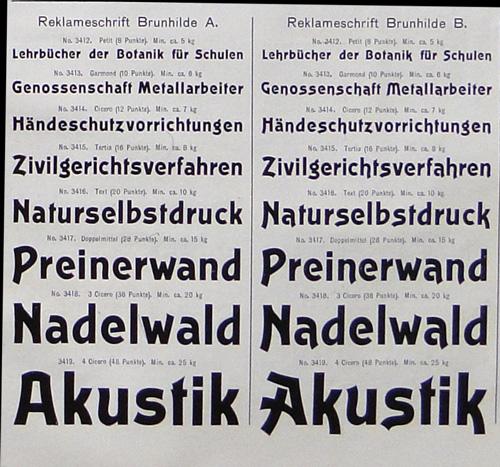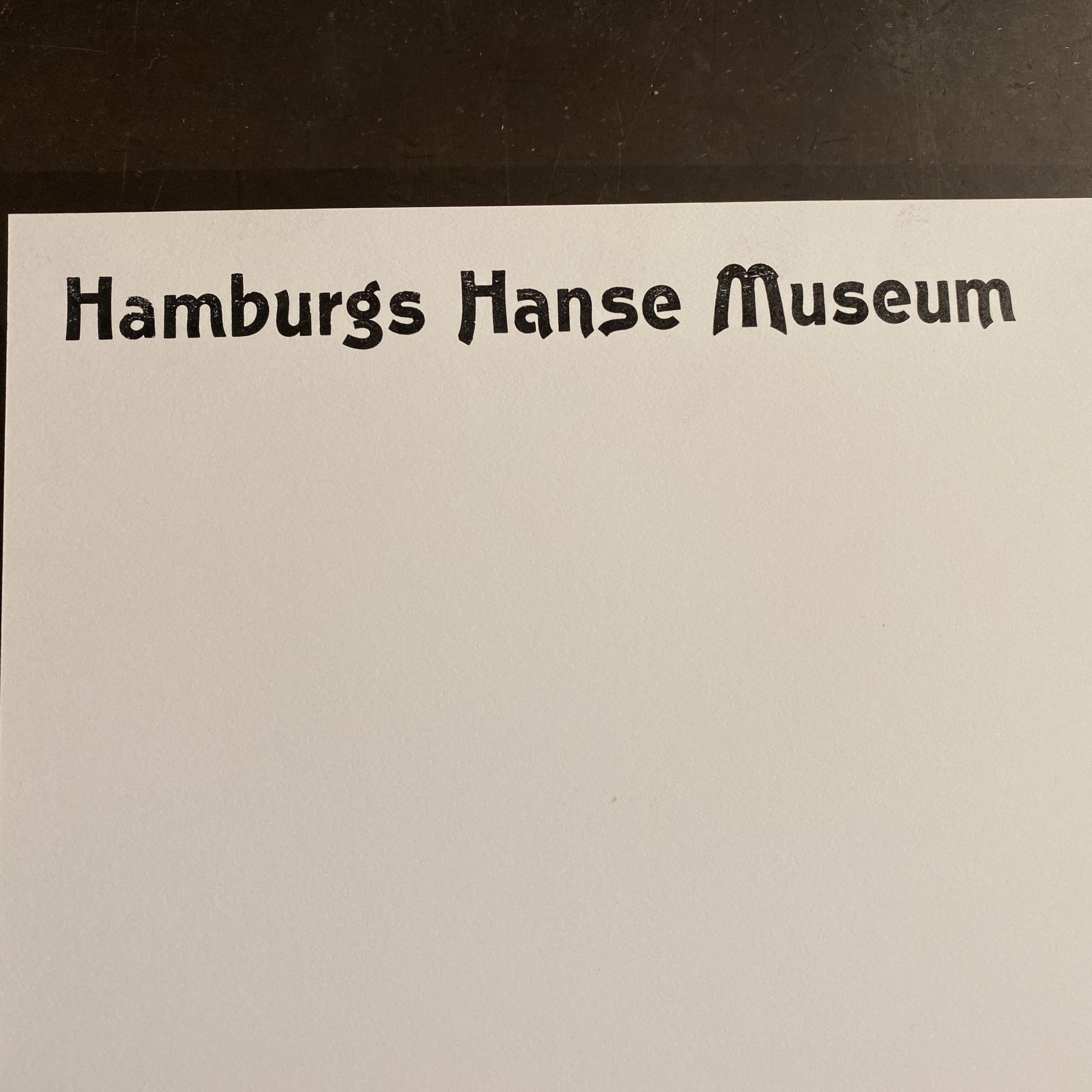
Hilfe bei Schriftidentifikation
nachdem meine Suche in den mir zugänglichen Schriftmusterbüchern nichts ergeben hat, versuche ich es auch einmal hier.
Kennt jemand von euch diese hier abgebildete Schriftart?
Ich habe extra mal ein paar der Alternativbuchstaben mitgedruckt, wie z.B. das Elefantenrüssel-m.
Hab Sie gefunden – Brunhilde Garnitur B.
Die Garnitur A hat diese alternativen Zeichen wie das offene a und runde M nicht.
Gab es von Rühl, Karl Brendler und sicher noch einigen mehr.
Hans Reichardt listet Sie auf und schreibt sie Ludwig Wagner zu.